השאלון עם נועה אולשבסקי
הכירו את נועה אולשבסקי. נועה היא ילידת 1996, גדלה בתל־אביב ושם היא חיה גם היום. נועה היא בוגרת המחלקה לתקשורת חזותית בשנקר, אותה סיימה בשנה שעברה, שם התמחתה במיתוג ובטיפוגרפיה – ״ואיכשהו כל פרויקט שלי נגמר סביב יצירת אותיות או פונטים,״ היא מספרת. למרות המעבר מעולם הפונטים לעולמות הארט והסושיאל, נועה מרגישה שהקו המחבר ביניהם ברור: ״אני אוהבת לשלב בין העולמות – לקחת רעיון, לארוז אותו גרפית לקמפיין או לפרויקט, ולמצוא את השפה הוויזואלית המדויקת בשבילו.״ מה שהכי מרגש את נועה בעיצוב הוא הרגע שבו רעיון הופך למוחשי – ״שהקונספט פתאום מקבל צורה, צבע או תמונה. ההבנה שעיצוב יכול לשנות תחושה, להאיר זווית אחרת או לגרום למישהו לחשוב, והדיוק בפרטים הקטנים הוא שעושה את כל ההבדל.״ כשנועה לא עובדת, היא מבשלת, אופה או מבלה בים.
היי נועה, מה שלומך? איפה אנחנו תופסים אותך השבוע?
סופ"ש רגוע בדירה שלי בתל־אביב. קצת ים, קצת חברים, קצת משפחה. משתדלת לנצל את הזמן הזה כדי להתנתק ולהבין מה חשוב לי באמת.
איפה את עובדת עכשיו?
אני מעצבת בסטודיו FUYA – סטודיו שעוסק בארט דיירקשן, קריאייטיב, סושיאל ומיתוג, בעיקר למותגי ביוטי. העבודה מגוונת מאוד ושונה ממה שחשבתי שאעשה אחרי הלימודים. חוץ מהעיצוב עצמו אני לומדת המון גם על עבודה מול מותגים מסחריים, ניהול לקוחות והבנה של צרכים עסקיים.
את מעדיפה לעבוד לבד או בצוות?
תלוי על מה. אני אוהבת לשקוע לבד במחקר ובפיצוח, אבל העבודה בסטודיו לימדה אותי כמה צוות יכול להיות מפרה, מפתח ומלמד.
מה הדבר הכי טוב שקרה לך השנה?
הפכתי לדודה. השנה הפכתי לדודה לראשונה, פעמיים – בהפרש של חודשיים! שני האחים הגדולים שלי הביאו לנו מתנות חדשות למשפחה. זה מרגש, מרחיב את הלב וגורם להבין מה באמת חשוב.
מזל טוב! מה גורם לך להתרגש ולעצב?
הרגע שבו רעיון הופך למשהו מוחשי. כשרואים קונספט שנולד בראש מקבל צורה, צבע או אות – ואיך הוא משפיע על אנשים. ההבנה שעיצוב יכול לשנות תחושה, לפתוח זווית חדשה או לגרום למישהו לחשוב, זה מה שמדליק אותי כל פעם מחדש.
מה את עושה כשאין לך מוזה?
אני חוקרת. קוראת, רואה, וחופרת בכל מה שמעניין אותי באותו הרגע. לפעמים אני מגיעה למאמרים ומקומות הכי הזויים ורחוקים מהנושא המקורי. בדרך כלל אחרי הצפה כזו של מידע אני פשוט מתחילה לעשות, גם בלי לדעת לאן זה הולך ומשם לאט לאט נוצר הקסם.
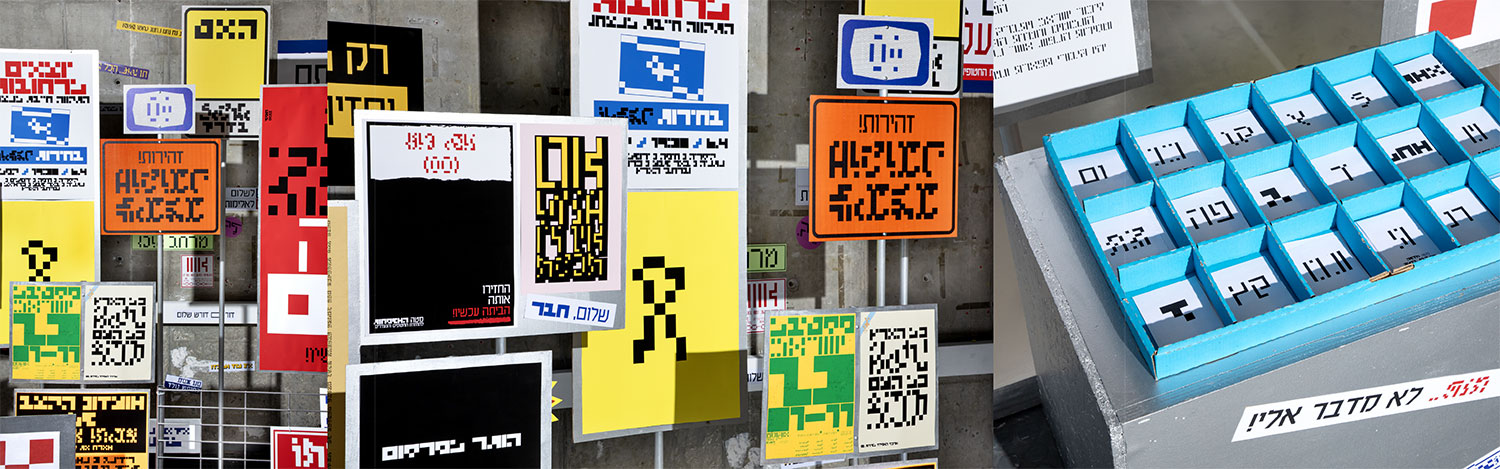
CommonSense – פרויקט הגמר של נועה אולשבסקי משנקר – בוחן את גבולות הקריאות והמשמעות של השפה במרחב הציבורי נוכח הצפת המסרים היומיומית. מתוך איסוף שלטים, סיסמאות וסטיקרים יצרה מערכת של שישה פונטים בהשראת דקונסטרוקציה של דרידה, הנעים מקריא לחלוטין ועד לא־קריא, כדי לחשוף מבני כוח סמויים ולהזמין ספק ופרשנות מחדש.
מה את עושה בשביל הכיף?
הולכת לים לבד.
יש לך הרגל מגונה?
לחשוב יותר מדי על כל דבר.
יצא לך לטייל בחו"ל?
טיילתי חצי שנה בדרום אמריקה, הייתי במזרח, באירופה ובארצות הברית. הטיול האחרון היה אחרי התואר וטסתי לחודש בתאילנד לבד. לא יודעת מאיפה היה לי את האומץ, אבל זאת הייתה חוויה מטורפת ומשנת חיים.
מה משך אותך לתחום?
מאז ומתמיד נמשכתי לעולמות האלה. גדלתי בבית יצירתי - לאמא שלי היה סטודיו לעיצוב בגדי נשים, אז זה תמיד היה חלק מהחיים שלי. בצופים הייתי זאת שרושמת את השלטים, ובתיכון למדתי במגמת אמנות. אחרי הצבא, רגע לפני הטיול הגדול, גיליתי דרך האינסטגרם שיש תואר בתקשורת חזותית, וישר ידעתי שזה מה שאני רוצה ללמוד.
לאן ניסית להתקבל ללימודים ולאן התקבלת?
ניסיתי להתקבל לבצלאל, לשנקר ול־HIT. לבצלאל לא התקבלתי, ובסוף בחרתי בשנקר.
איזה מרצה השפיע/ה עלייך במיוחד?
שאלה לא פשוטה, מכל אחד ואחת מהמרצים למדתי משהו, וקיבלתי כלים ופרספקטיבות שונות גם על עיצוב וגם על החיים. החוויה הכי משמעותית שהכי השפיעה עלי בלימודים הייתה פרויקט הגמר בהנחיית עידן עם־שלם ויעל בודשר. הם ליוו אותי ברגישות ובחוכמה – ואין ספק שלא אשכח אותם.
במה היית עוסקת אם לא היית מעצבת?
כנראה במשהו טיפולי. התחום הזה מסקרן אותי מאוד, אני שואבת ממנו השראה והוא מתחבר לי לרגישות – בדיוק כמו בעיצוב.
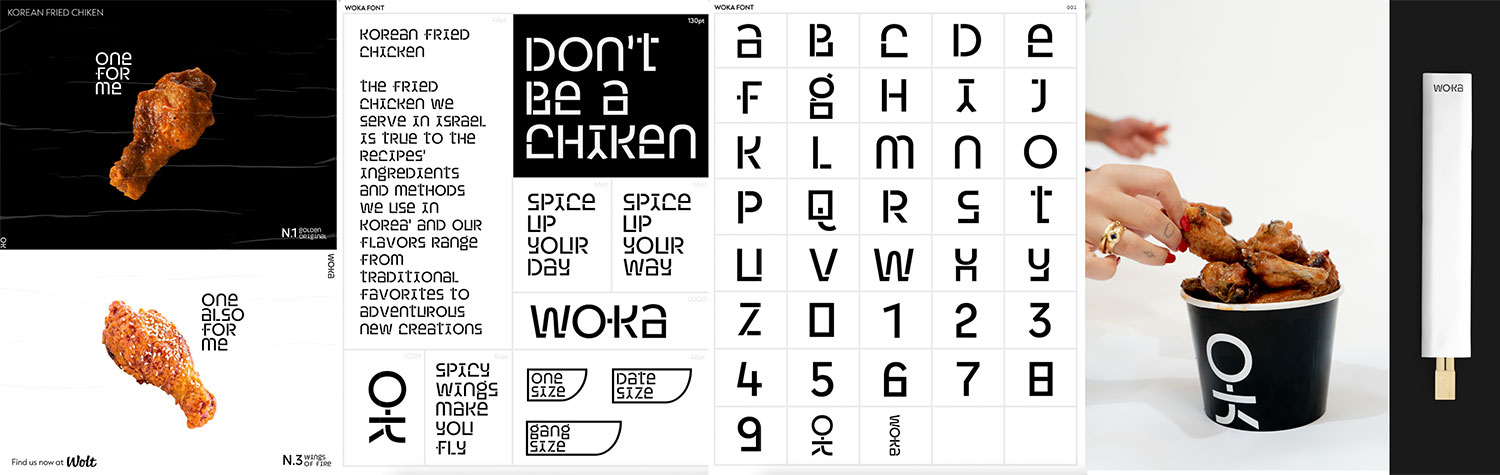
WOKA – מיתוג למסעדת עוף קוריאני מטוגן שנוצר בקורס מיתוג מתקדם בהנחיית יעל בודשר – נשען על המפגש בין חדשנות למסורת, מזרח–מערב ואוכל רחוב–ביתי. נועה פיתחה את WOKA Font, פונט לטיני בהשראת האותיות הקוריאניות, כדי לבטא שפה גלובלית עם שורשים מקומיים. השפה הצילומית והקופי הקליל מייצרים מותג צעיר, שובב ואורבני – עם עומק תרבותי שמחבר בין סיאול לתל־אביב.
איפה את רואה את עצמך בעוד חמש שנים?
אני מנסה לא לחשוב על זה יותר מידי. אין לי מושג איפה אהיה, אבל אני יודעת שכל עוד אני ממשיכה לדייק את עצמי ולשאול את השאלות הנכונות – אגיע למקום המדויק בשבילי.
ספר אחרון שקראת?
״אולי כדאי לך לדבר עם מישהו״ – לורי גוטליב. ספר מהמם שמספר על טיפול פסיכולוגי משתי זוויות: הפסיכולוגית שמטפלת במטופלים, ובמקביל היא בעצמה בטיפול. זה נותן פרספקטיבה כפולה, משלב תיאוריות מעניינות, מצחיק, מרגש וגורם להבין שכולנו עוברים בסוף את אותם הדברים.
רוצה להמליץ על ספר עיצוב?
"Grid Systems in Graphic Design" של Josef Müller-Brockmann – ספר קלאסי שתמיד חוזרים אליו.
אתר השראה מדליק שאנחנו לא מכירים?
It’s Nice That – תמיד מפתיע, מגוון, ומביא השראה מזוויות שונות.
באיזה פונט היית רוצה שיכתבו על המצבה שלך?
Sunday של מיכל סהר.
קיצור מקלדת אהוב?
Find – ⌘F